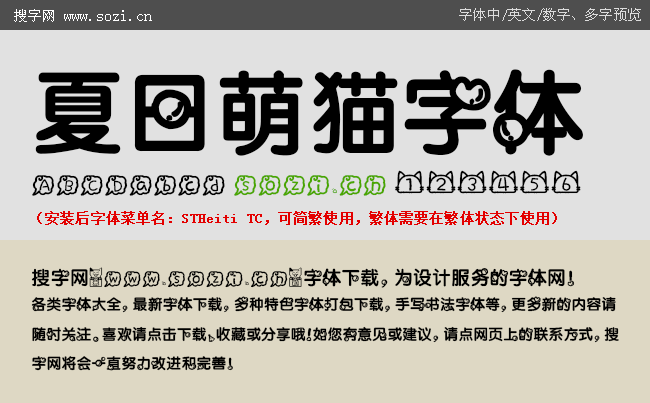
夏日萌貓字體
搜字網(wǎng)給大家提供一款很有趣的手機(jī)中文字體下載。修改者給他起名為夏日萌貓字體,這款手機(jī)字體是在粗圓體字體筆畫間插入了可愛的卡通圖案。在具備粗圓字體醒目清晰端正的風(fēng)格同時(shí),卡通味也特別濃,是一款非?蓯鄣目ㄍㄗ煮w,特別適合喜歡手機(jī)字體個(gè)性一些的朋友在手機(jī)上安裝使用。